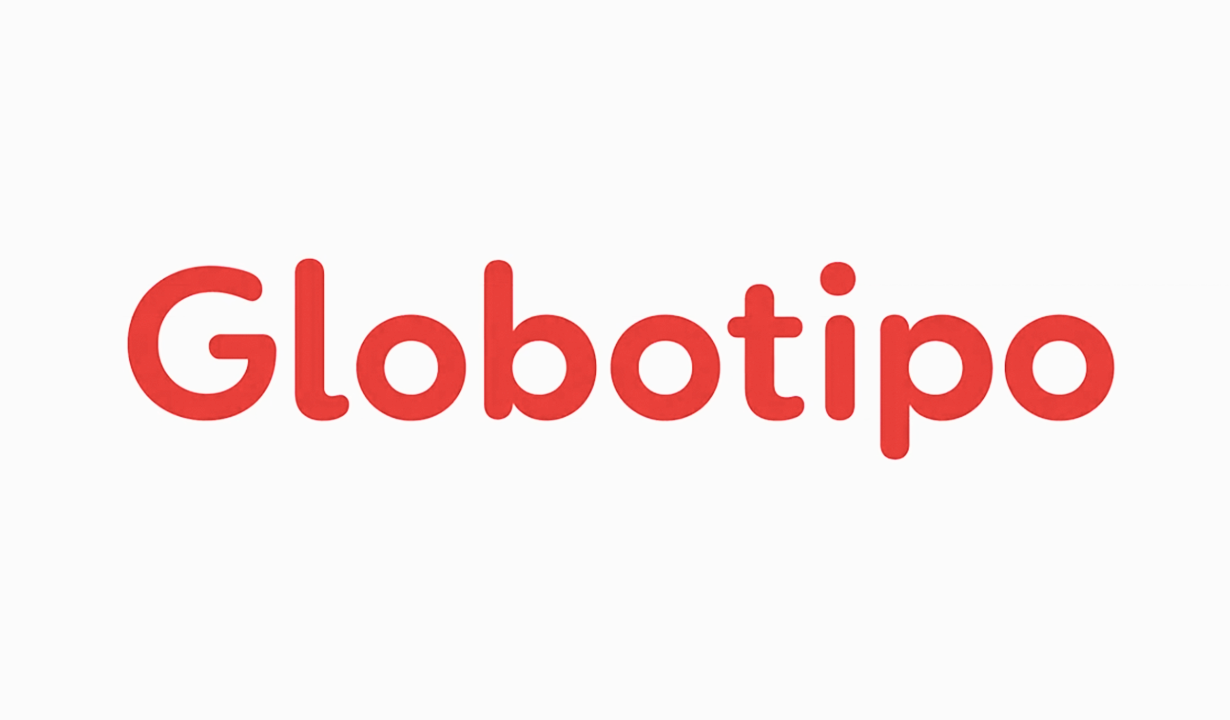
A Rede Globo, em parceria com o estúdio Plau, lançou uma nova tipografia que conta com mais de 30 fontes exclusivas para a emissora. Para a reformulação, a emissora queria uma tipografia global, multiplataforma e flexível.
As fontes têm raízes geométricas, presentes em outras do gênero como Futura, Avenir, Gotham e Proxima Nova. Sua largura é generosa e seus redondos tendem ao circular geométrico presentes no símbolo da Globo.
As aberturas das letras são amplas, o que é um dos pontos de diferenciação fundamentais em relação à família anterior. Os cortes de terminação são 100% verticais e criam um ritmo de leitura organizado e sóbrio.
Um dos passos fundamentais foi pensar na melhor exibição possível em situações de baixa resolução ou em sistemas de rasterização específico, caso do Windows.